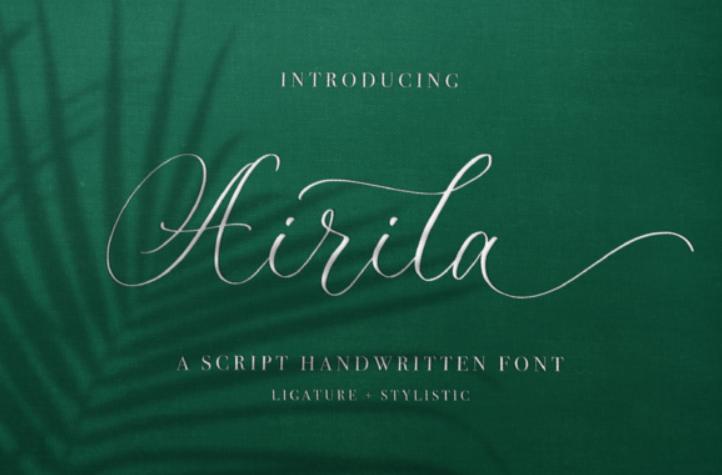
Airila - очаровательный рукописный шрифт. Этот универсальный скриптовый шрифт имеет широкий спектр применения, от поздравительных открыток до заголовков. Airila имеет кодировку PUA, что означает, что вы можете легко получить доступ ко всем глифам и росчеркам...